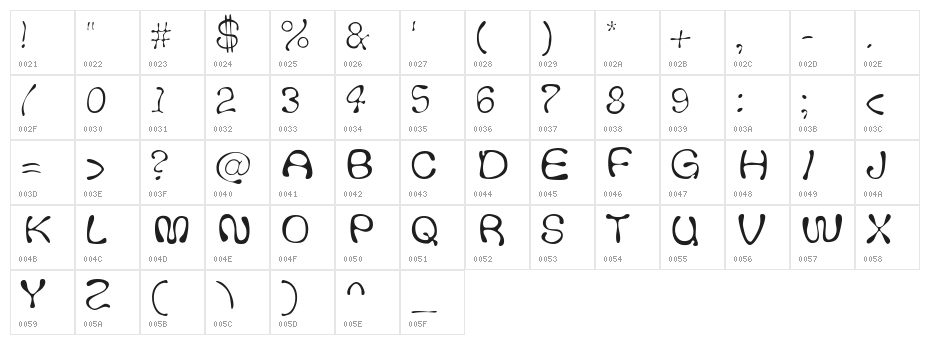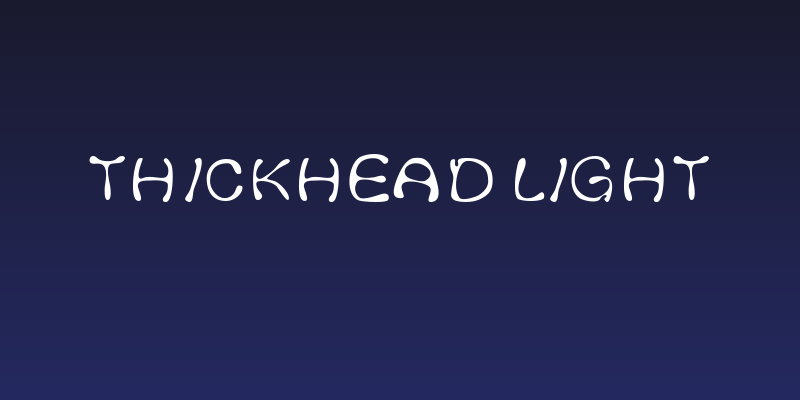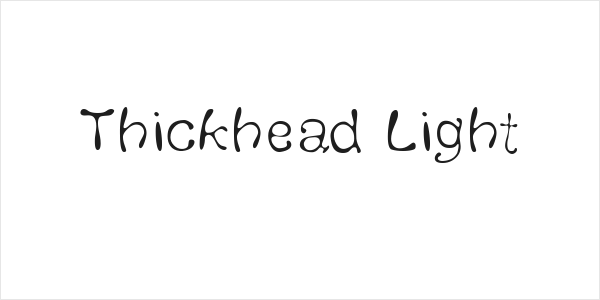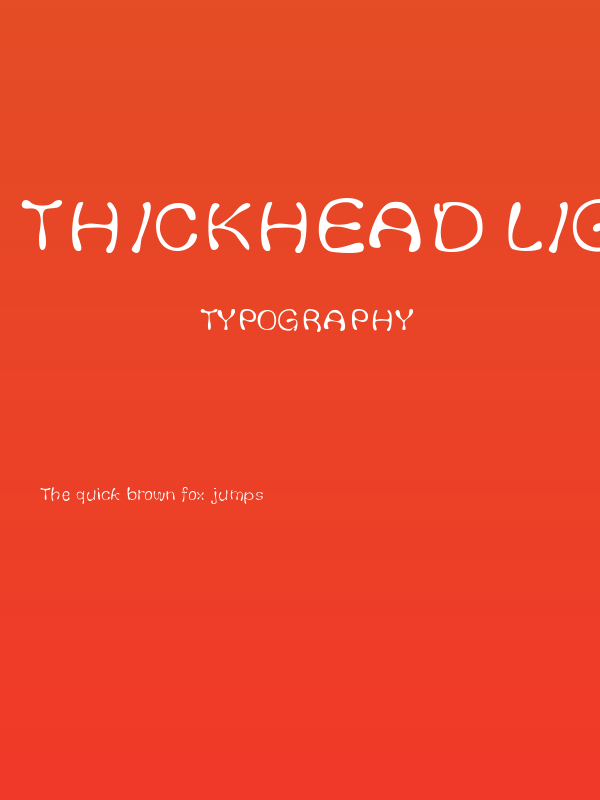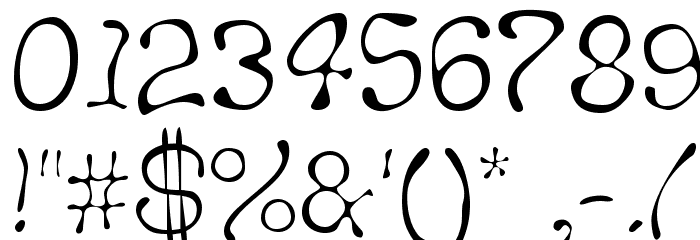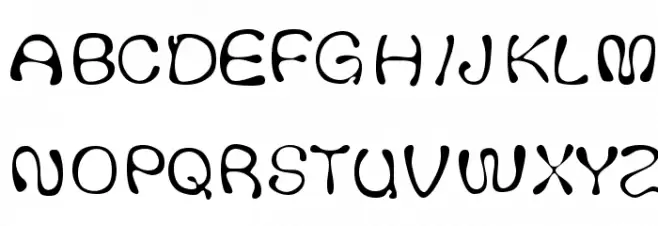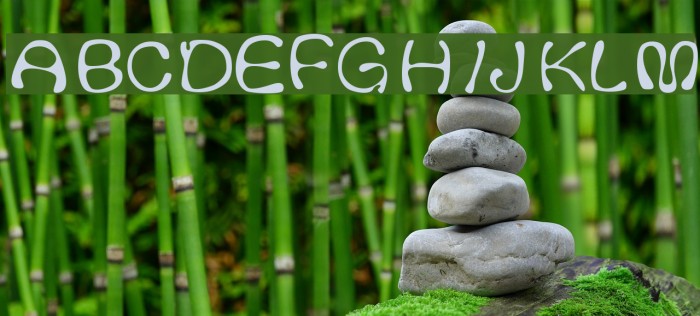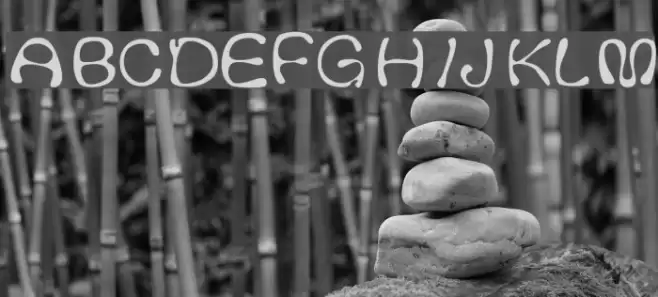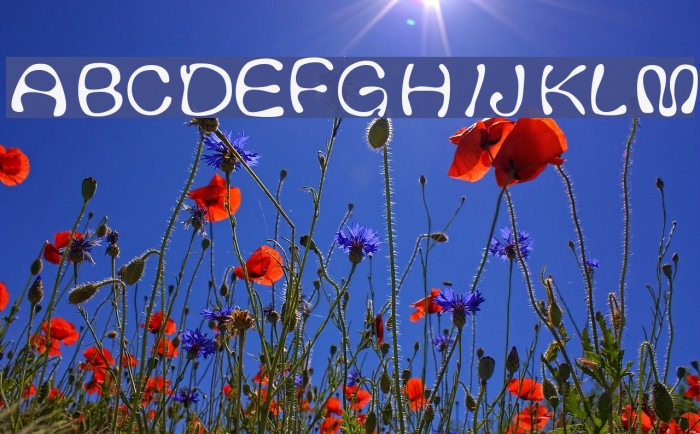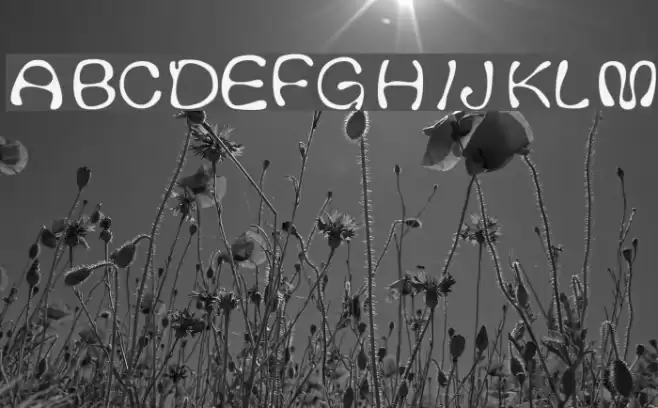
Thickhead Light Font
| Estilo geral | Playful |
| Caso de uso | Headlines, Logos, Creative Designs |
| Projetos propostos | Ideal for children's books, playful branding, artistic posters, and creative designs. |